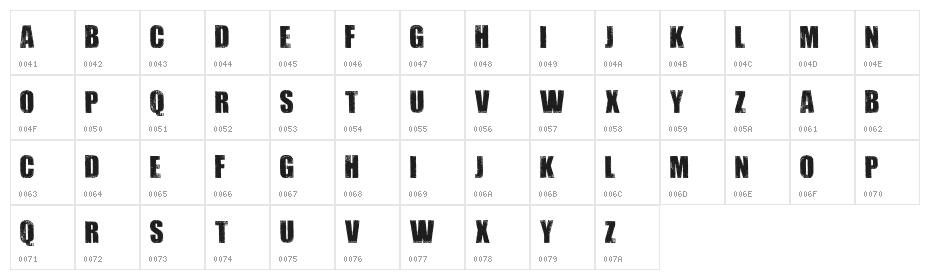
DIRTYBAG BOLD TRIAL Font
✎ Messy
| Gesamtstil | Vintage |
| Vorgeschlagene Projekte | Ideal for posters, album covers, branding for rugged products, or any design needing a vintage or industrial touch. |